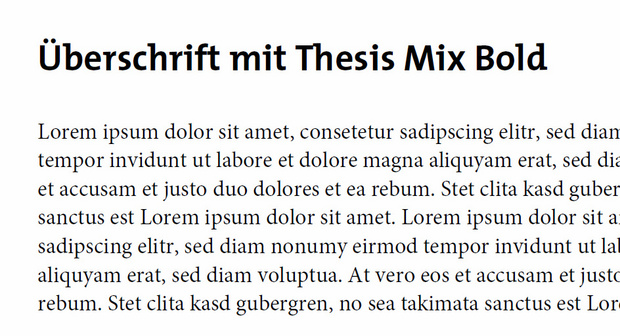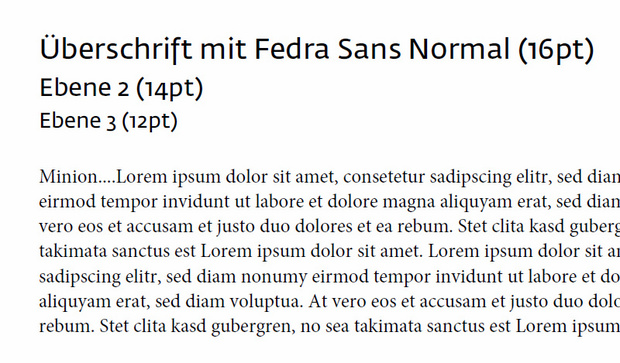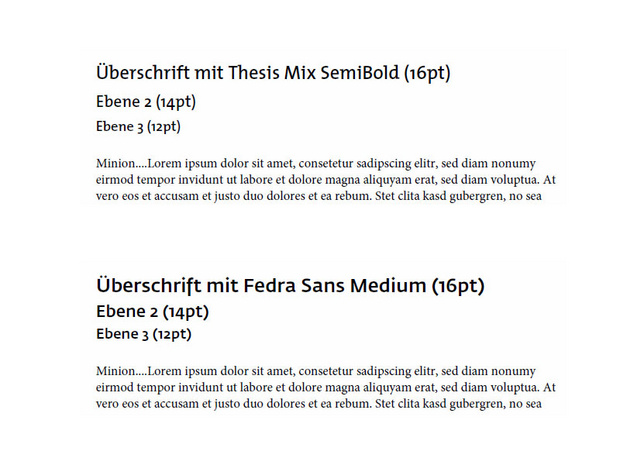
Minion + Thesis Mix ?
in meiner wissenschaftlichen Arbeit verwende ich Minion für den normalen Text.
Für die Überschriften verwendete ich bisher Frutiger. Irgendwie hätte ich gerne einen neuen Anstrich. Was haltet ihr von dieser Kombinationen:
Minion + Thesis Mix (Bold)
Beisst sich diese Kombination eurer Meinung nach? Die Thesis Mix wirkt ein wenig wie eine Slab Serif, dadurch, dass sie eine Mischung aus Sans und Serif ist. Eine Frutiger oder Avenir trennt beide Schriften deutlich voneinander ab... Trotzdem gefällt mir die Thesis!
Freue mich auf weitere Tipps.
kann ich mir gut vorstellen, dass das klappt. grundsätzlich gemeinsame formensprache (humanistisch), gleichzeitig klare differenzierung (semi-slabserif / antiqua).
der erfolg/misserfolg des vorhabens liegt dann wie immer in der konkreten typografie.
wenn du uns was zeigst, sagen wir gerne was dazu.
So würde es aussehen
Da würde ich entweder die Größe der Überschrift reduzieren oder sie einen Schnitt dünner machen. Oder sogar die Größe der Überschrift reduzieren und sie einen Schnitt dünner machen.
Hier mal der Versuch mit einer kleineren Schriftgröße und einem dünnen Schnitt.
Zum Vergleich noch eine Version mit Frutiger.
Ich bin leider kein Typografie-Experte, befürchte aber dennoch, dass die Minion-ThesisMix Kombination nicht wirklich harmonisch ist... Was sagt ihr Experten dazu?
Ich finde, dass sowohl TheMix als auch Fedra Sans einen guten Kontrast zur Minion bilden. Jedoch würde ich eher einen Medium- bzw. Semibold-Schriftschnitt der TheMix oder Fedra Sans verwenden.
Würde dann so aussehen. Kann mich absolut nicht entscheiden.
Thesis wirkt auf mich zeitlos, Fedra hingegen hat für mich einen technischen Charakter (was zum Themengebiet meiner Arbeit auch passen würde). Die Thesis macht sich nicht so breit wie die Fedra...
Die Entscheidung kann dir keiner abnehmen.
Ich würde mich wohl eher für die Fedra-Sans- und Minion-Kombination entscheiden. Die wirkt auf mich bedeutend frischer.
ich würde themix nehmen (auch wenn ich sie grundsätzlich nicht sehr liebe). die fedra sans wirkt auf mich viel zu gedrungen und behäbig neben der schlanken minion. die x-höhen harmonieren überhaupt nicht – und das fällt (mir) störend auf, auch wenn die beiden schriftarten nicht auf einer zeile stehen. außerdem kann ich nicht nachfühlen, wieso die fedra technischer wirken soll; auf mich macht sie eher einen teigigen, gediegenen eindruck. die fedra sans condensed wäre mir wiederum zu schmal. außerdem hast du bei themix mehr schnitte zur verfügung, insbesondere einen semilight-schnitt, den du zumindest für die oberste ebene gut gebrauchen könntest.
Eine weitere Kombination ist meiner Meinung nach mit Minion (Fließtext) ITC Franklin Gothic (Überschriften, Tabellen, etc.) und Avenir (Überschriften, etc.) möglich. Eine gute Alternative zu Frutiger/Helvetica (für Überschriften).